2022 年最佳免費字體
已發表: 2022-04-06您是否知道在線提供諸如開源、免費用於商業用途的字體之類的東西?
對於想要使用獨特字體來創建獨特的品牌外觀的品牌來說,這是一項巨大的資產,而不僅僅是與其他所有字體融為一體。 您可以使用這些獨特的字體而無需向設計師支付高額費用,同時仍確保您在大多數比賽中脫穎而出——尤其是如果比賽仍然使用他們文字處理軟件中的平淡默認字體!
想看看您可以為您的業務利用的一些最佳字體嗎? 讓我們來看看 2022 年可用於商業用途的最佳免費字體。
1.抵抗Sans
我們想在 2022 年看到的第一個免費字體是 Resist Sans。
這是一種非常乾淨、現代的字體,適用於許多不同的品牌。 我們可以看到這對於簡單的 SaaS 品牌或更專業的環境(如非營利組織或律師事務所)來說效果很好。
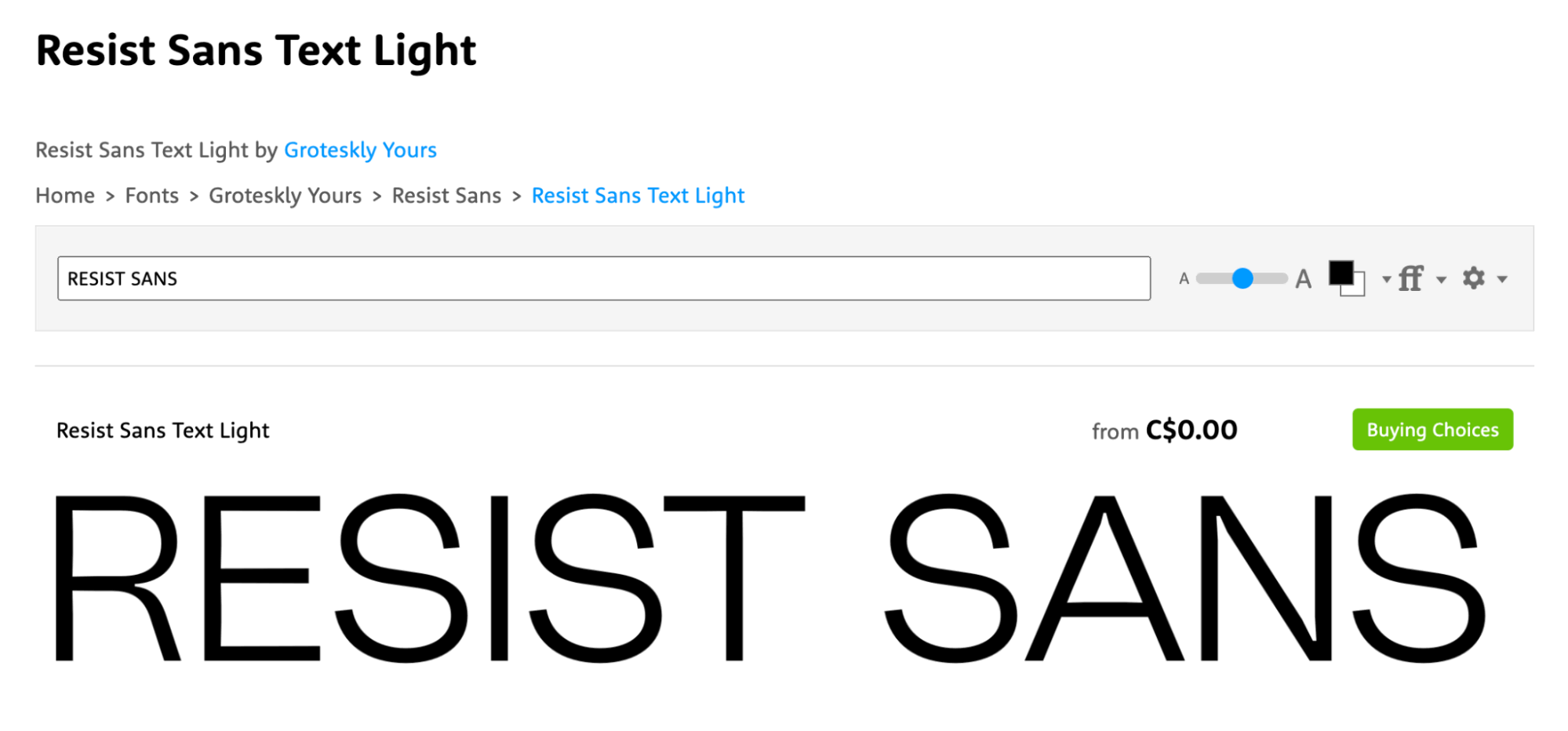
雖然這種字體不一定會像我們將在此列表中看到的其他一些更獨特的選項那樣以創造性的蓬勃發展脫穎而出,但它仍然是獨特且安全的選擇。 以“少即是多”為主題,這種簡約的干淨字體在您使用它的任何地方都不會看起來很糟糕。
2. 雷霆
Thunder 字體是塊狀的,風格很重。 它在粗體和常規格式中看起來都很棒,如下圖所示,兩者之間的差異可能很大,有助於創建視覺平衡的設計。
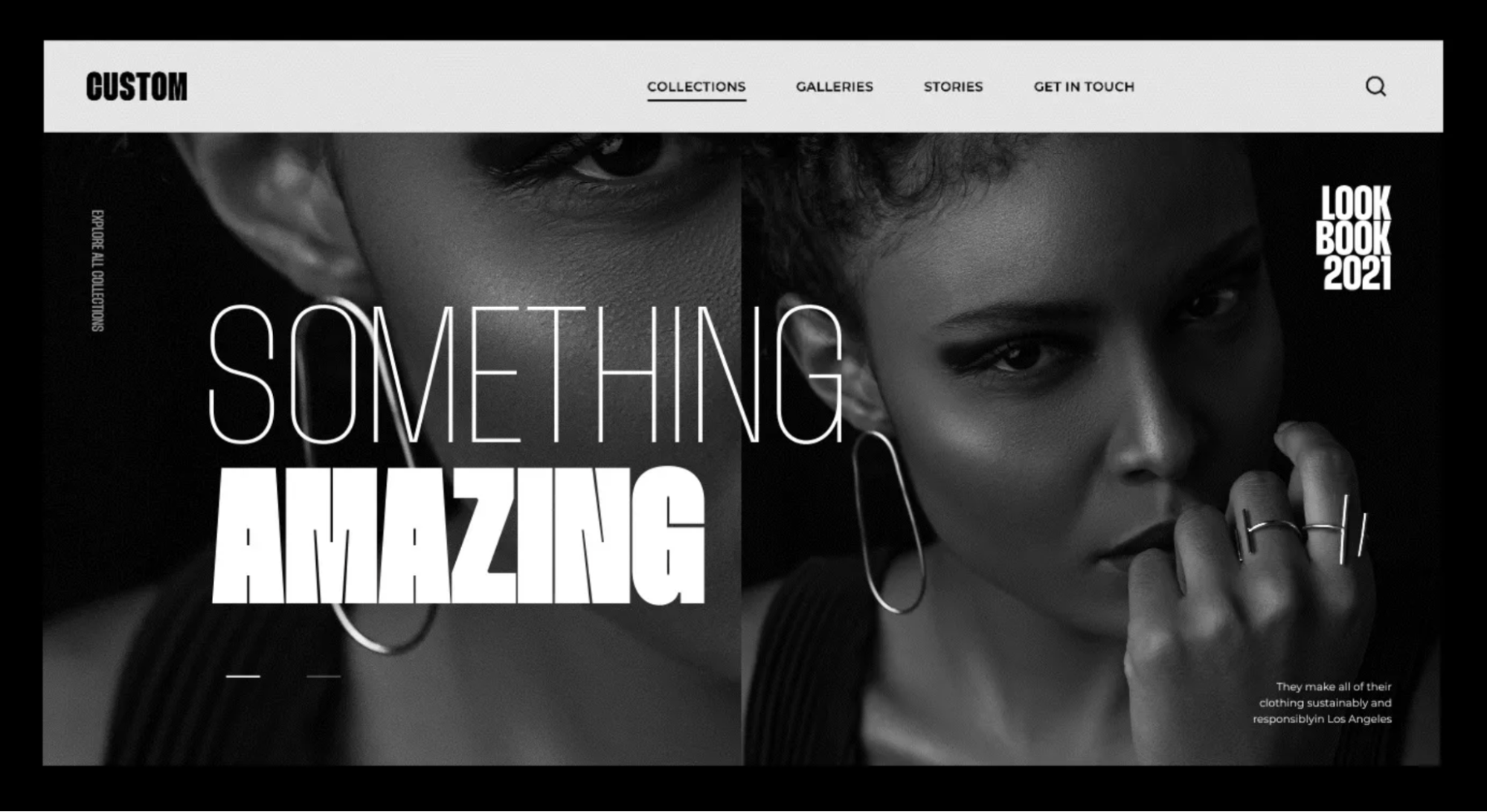
因為這種字體比較古怪,它非常適合創意品牌,比如時尚行業的品牌。
3. SuperDuper
SuperDuper 具有長而有棱角的藝術字母,這些字母足夠微妙,看起來很專業,同時仍然具有獨特的光暈。 您可以在下圖中的“S”中真正看到這一點,其中有多個角度轉彎。
因為它很有趣,同時仍然非常容易閱讀,所以這將是品牌視覺效果的絕佳選擇; 不用擔心用戶是否可以在縮略圖中閱讀它,但他們仍然可以肯定地識別它。
4. 恢復
Restora 是一個更加女性化的文本,具有非常獨特的特徵。 這是一款帶有現代風格的老式襯線字體,具有棱角分明的曲線和強烈的易讀性。 您可以在下面的 M 和 N 以及 R、P 和 C 中看到較粗的曲線。
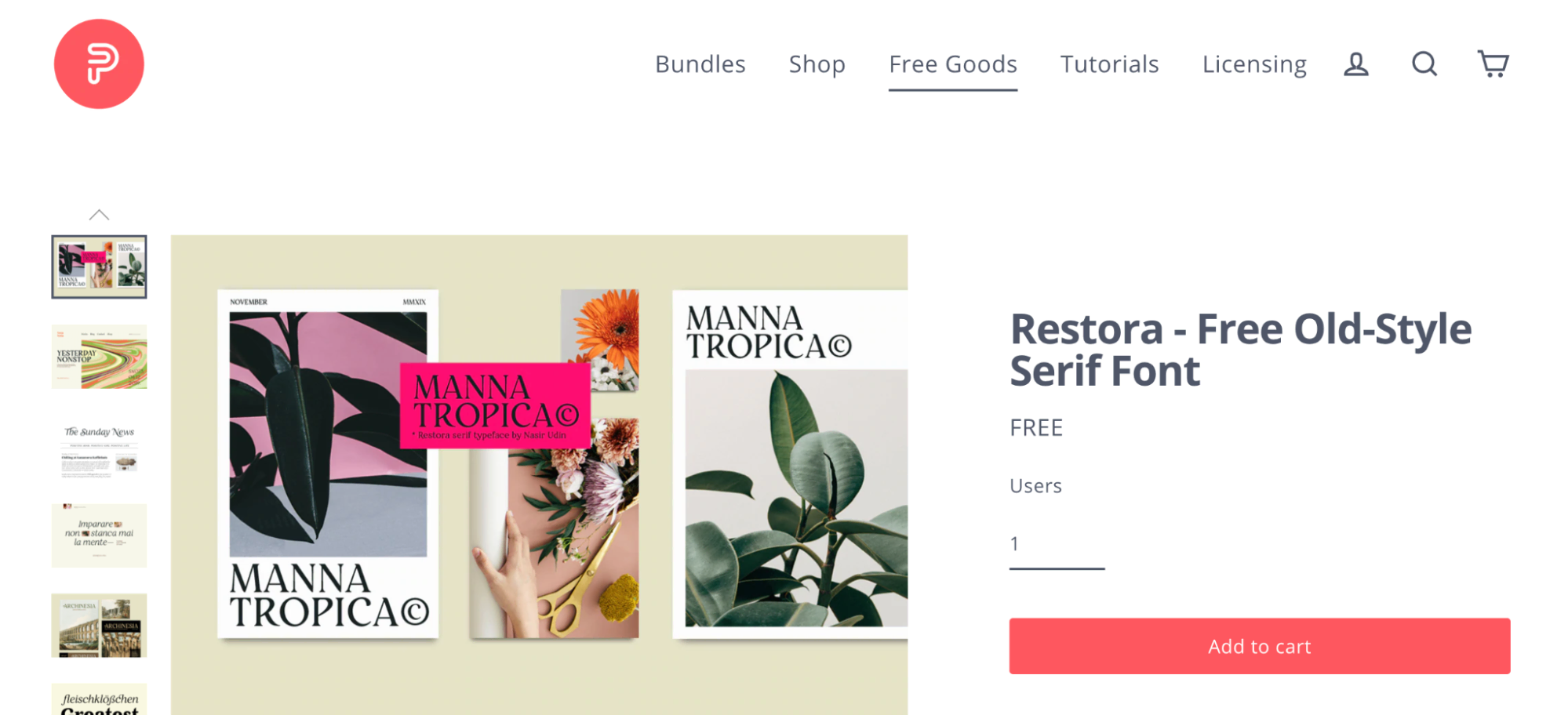
漂亮、現代、女性化、有點熱帶風情,我們可以看到這種字體在時尚、化妝或電子商務品牌中表現得非常出色。
5. 哽咽
當我讀到這種字體的名稱時,我絕對會死,部分原因是它太合適了。 Chonk 字體非常重視它的名字(開玩笑) ,字體非常厚實,非常塊狀。
這將是一種有趣的字體,可用於使信息圖表或社交媒體圖形更加生動。 我們可能不建議使用這個來進行品牌推廣,因為這些字母非常塊狀,除非您只需要一個特定的字母來代表您的品牌,否則它們很難在小徽標和縮略圖中閱讀。
6.巴斯特爾
毫無疑問,Basteleur 是一種非常獨特的創意字體。 你見過像下面這樣的“a”嗎? 可能不完全。
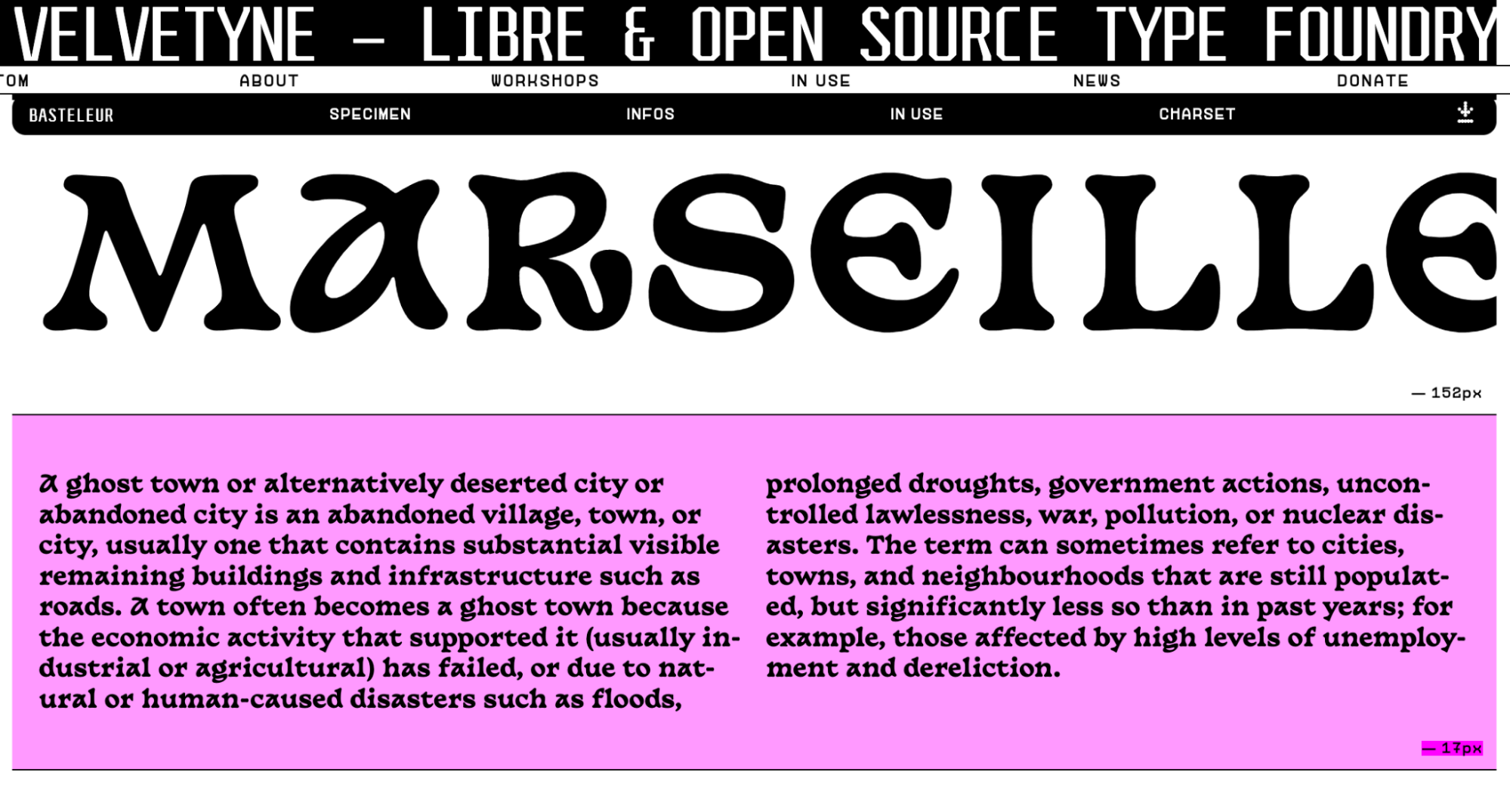
我喜歡這種字體的一個原因是它具有曲線美和藝術感,同時仍然具有塊狀的吸引力。 在幫助您的品牌脫穎而出的同時,它仍然很容易閱讀。
7.中性臉
這種圓潤、乾淨、纖細的字體看起來既現代又風格化。 天空是這個字體的極限,這就是為什麼它是我們 2022 年最好的免費字體之一:無論你想如何使用它都會看起來很棒,使它成為一個安全但仍然有趣的選擇。
8. 畜牧業
Faune 具有很強的創意天賦,只是略微偏離的比例立即吸引了用戶的眼球。 作為社交媒體圖片中的標題或品牌網站的標題,這看起來很棒。 這裡有很多選擇,但只要確保它符合您品牌的整體審美。
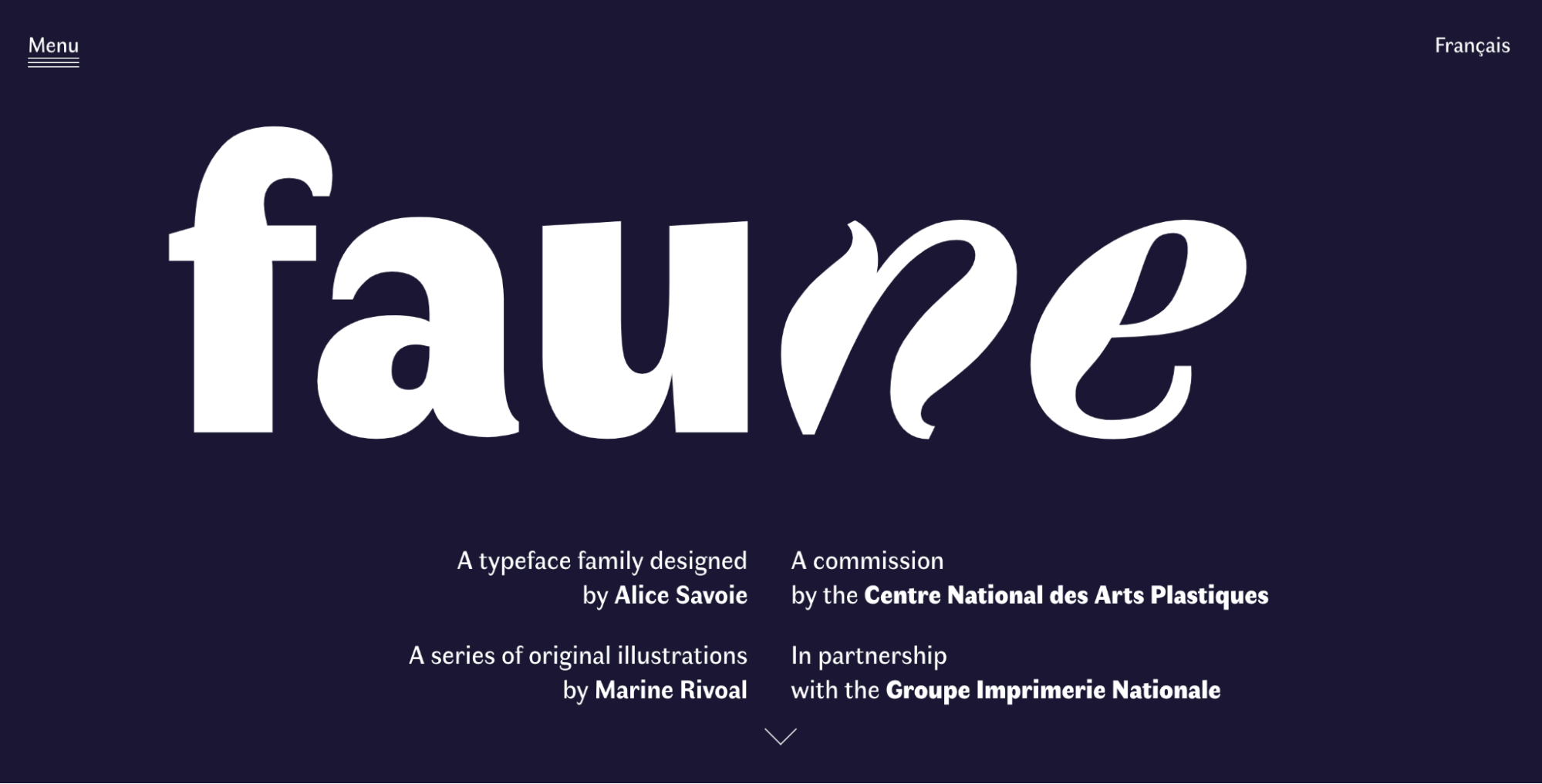
9.中本聰
想要一些乾淨簡單的東西,不會過於突出,但看起來仍然專業且有點不同?
中本聰可能是一個完美的選擇,正是您正在尋找的。 與您在大多數文字處理軟件中看到的許多字體相比,這種字體看起來更高端一些,而且它超現代且完全“不引人注目”。 對於您的在線內容來說,這是一個簡潔的極簡選擇。 此外,它似乎以比特幣的神秘創造者的名字命名,值得加分。
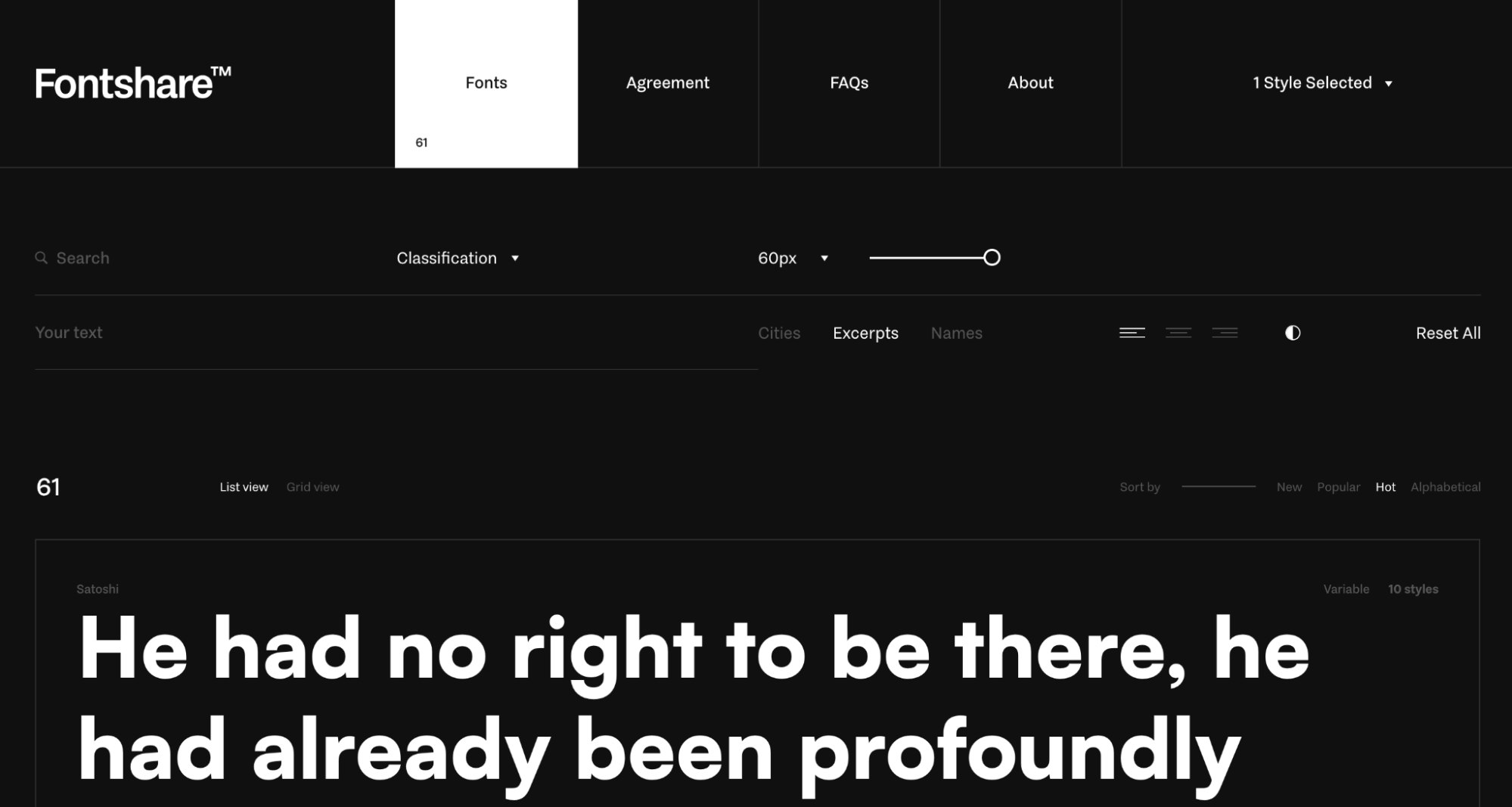
10. 邦克
如果您喜歡 angular-meets-caligraphy 風格,Baunk 可能會很快引起您的注意。 這是一種未來主義字體,我們絕對可以看到它也適用於電子商務、B2B 和科技品牌。
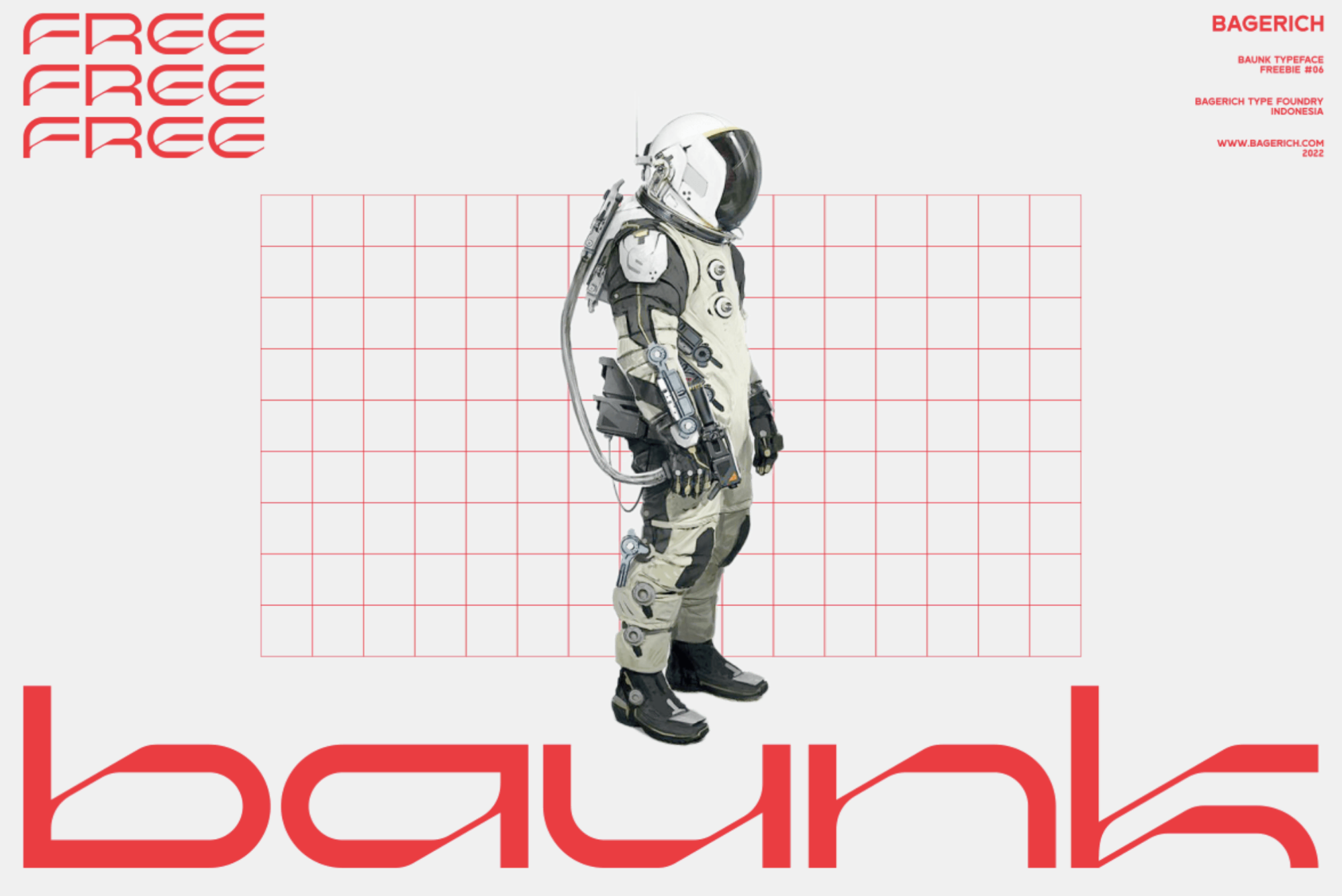
需要注意的一點:這可能很難在 YouTube 縮略圖上閱讀,因此在選擇徽標或設計時請記住這一點。
11. 中心
尋找另一種超時尚的字體? Centrion 只是感覺它屬於電子遊戲。 憑藉其戲劇性的華麗和動態的手寫感覺,這是一個明智的選擇。 如果你有一個會吸引觀眾的觀眾,這是一個很好的考慮。
12. 窄檔案
Archivo Narrow 是另一種簡單、中肯的字體,無論您想如何使用它,它看起來都很棒。 沒有人會說這不專業並且不容易閱讀,這是品牌需要考慮的兩個重要特徵。
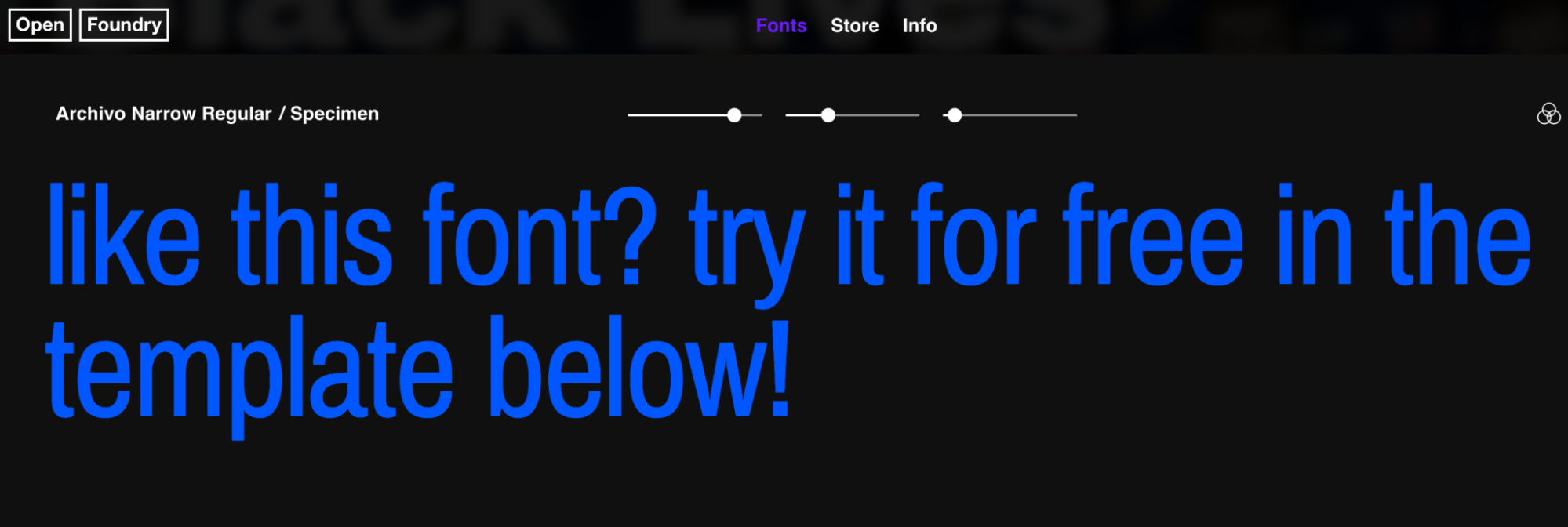
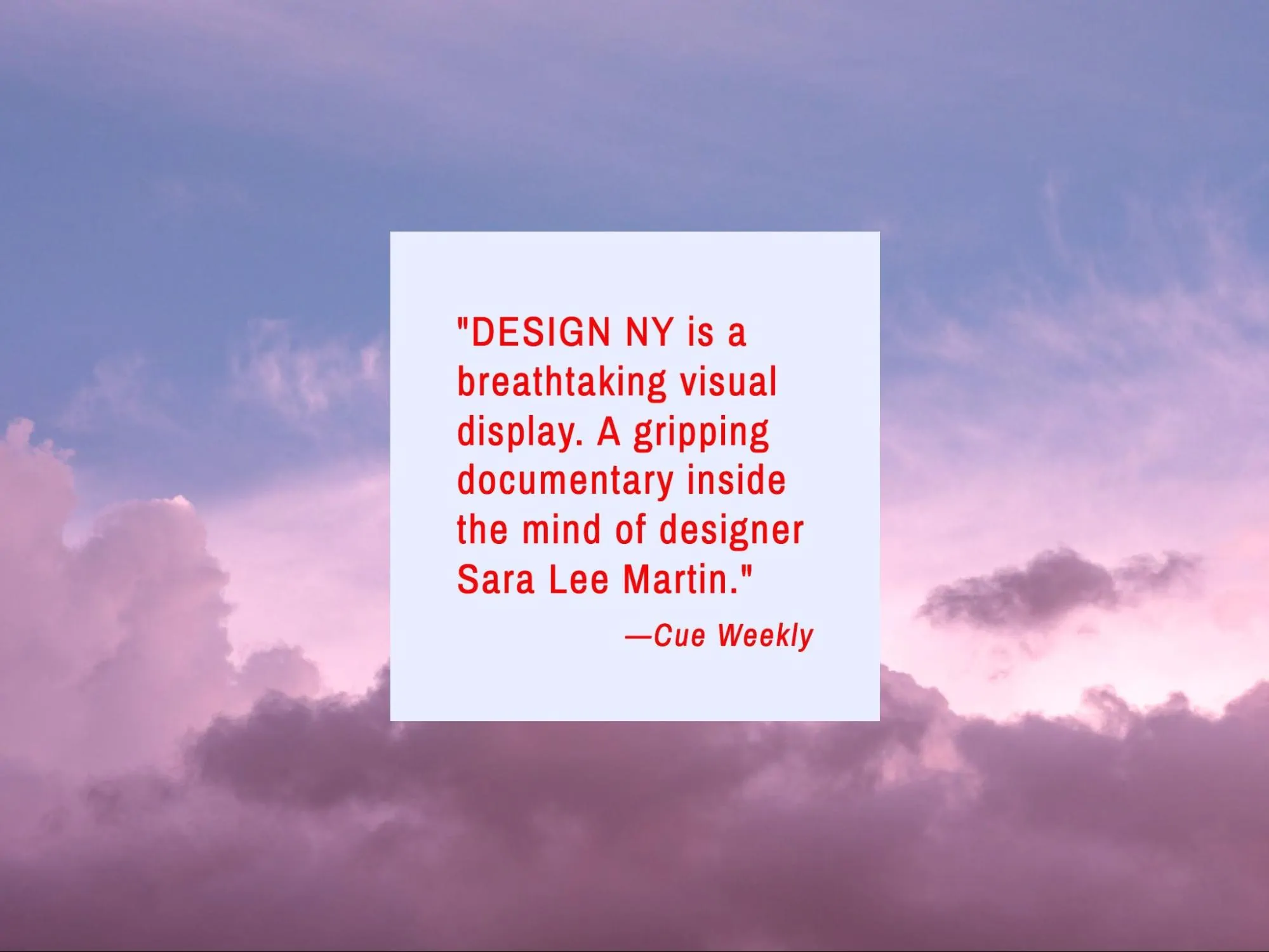
字體有時被視為事後的想法,但您選擇的字體會對客戶如何看待您的品牌產生巨大影響。 它還有助於建立品牌知名度和認知度,這兩者對企業都至關重要。